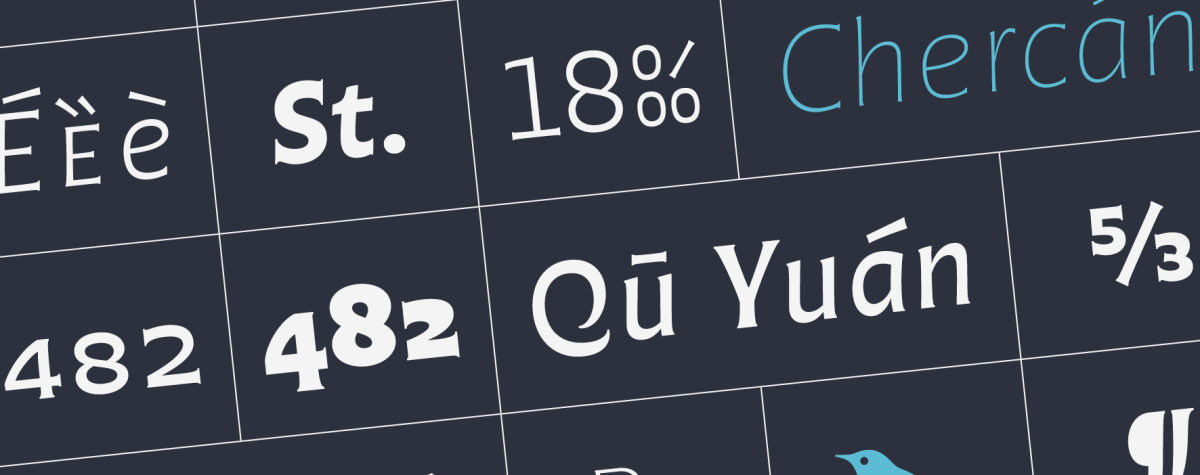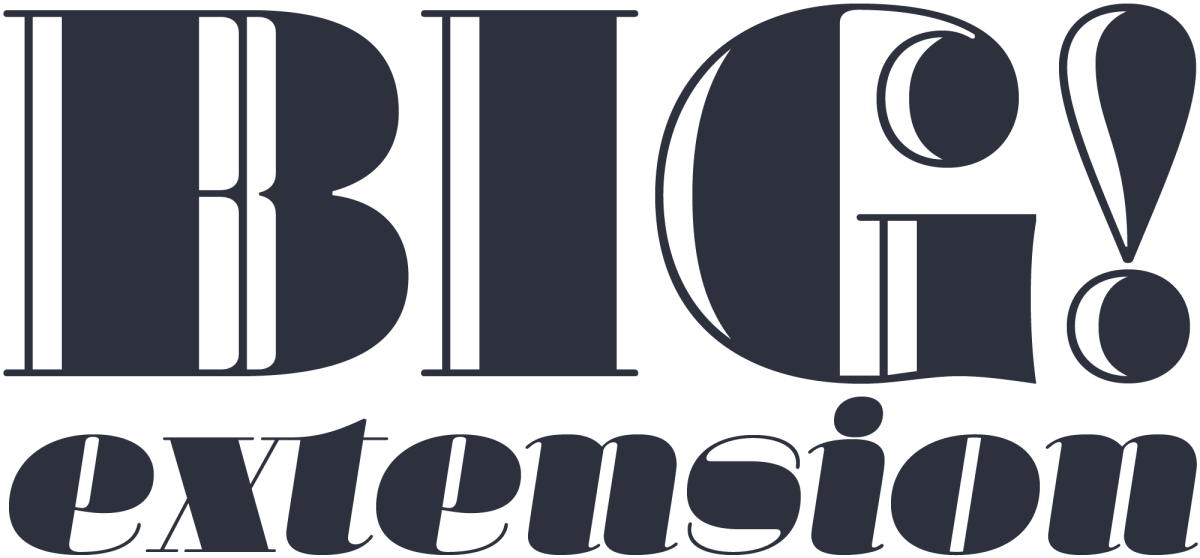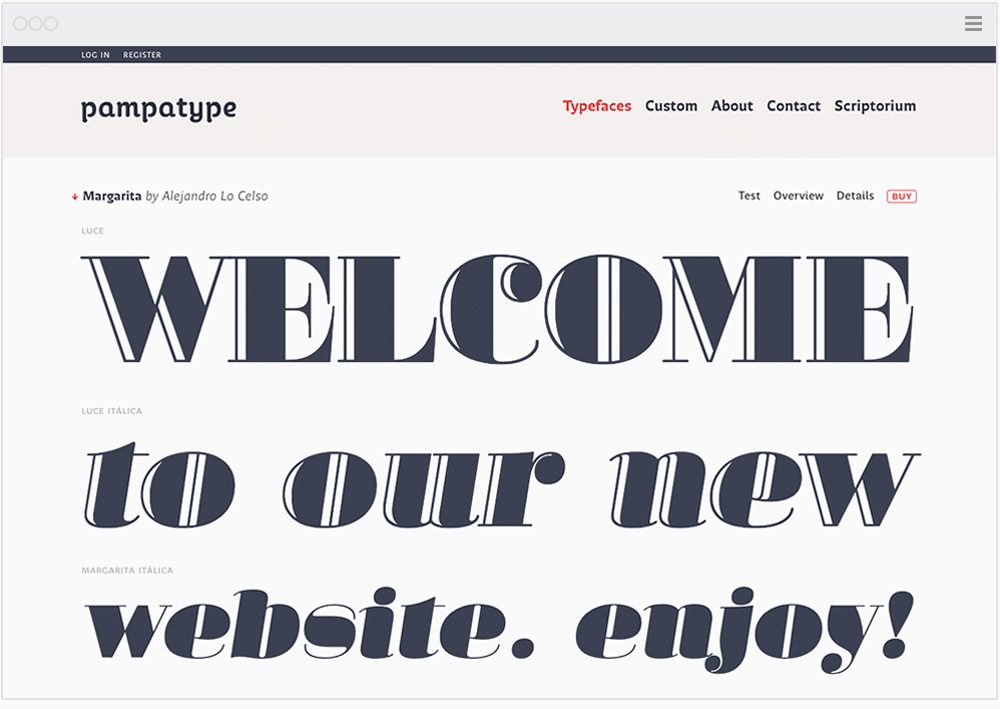
«Hacer y componer» de Francisco Gálvez (Editorial de la Universidad Católica de Chile) es, sin duda, un libro pedagógico. Como afirma Alejandro Lo Celso en el prólogo, se trata de un trabajo generoso, en el que se percibe la experiencia del autor en su actividad profesional. Como diseñador, tipógrafo, calígrafo y docente. Y, desde luego, esa generosidad se agradece. Read
We are proud of this project: The design of a typeface for the Universidad Nacional de Córdoba in Argentina, an educational institution of more than 400 years, the first in the country and one of the earliest in the continent. As part of the celebration for the hundred years of the University Reform, which occurred in this house in 1918, the UNC commissioned PampaType the design of a typeface to address their multiple communication needs. The resulting design, ‘Reforma’, is a multi-form family with diverse styles. In this article we share a bit of context, all the design process, some of our drawings and production details, and a few insights harvested throughout this 3-year fruitful experience. Read
Hoy en día los diseñadores somos responsables de una parte de la producción editorial que durante siglos había recaído en manos de especialistas: la composición tipográfica. Lamentablemente la evidencia indica que, en general, ésta sufre de un promedio de calidad mediocre. El problema no reside en las herramientas que tenemos a nuestra disposición —el software que usamos hoy día nos permite no sólo igualar, sino sobrepasar la calidad de la composición tipográfica de los siglos anteriores—; estriba en desaprovechar su potencial y, sobre todo, en no estar siquiera conscientes de que hay algo que necesita mejorar. Como nos recuerda Antoine de Saint-Exupéry, “lo esencial es invisible a los ojos”. El presente texto analiza esta cuestión y muestra la manera de resolverlo, mejorando la calidad de nuestro trabajo y reduciendo el tiempo invertido. Read
This typeface is named after the astonishing guitar player and singer Atahualpa Yupanqui, a central figure to Argentine folk music. ‘Don Ata’, as he was called, was a wise poet with a particularly sensitive view of the elements of nature as well as of the human condition, all of which he turned into compelling lyrics and magic songs. For years I dreamed about designing a typeface in his name. I imagined a firm, rough voice, though interpreted with delicate curves and a feel of warmth. After a few years of occasional sketching finally a spirit aroused in 2014. The initially vague forms turned into precise letterforms and with time into a family of fonts. Now the type Atahualpa finally sees the light. I’m happy. Here I invite you to unveil all the secrets behind the scene, discover the clues of the inspiration and the design process, and enjoy some footnotes from our design kitchen. Read
El universo de la tipografía está lleno de sutilezas y detalles, de formas que transmiten ideologías a través de sus trazos. El espécimen tipográfico es el mundo que antecede a la puesta en página y donde sobran pretextos para observar el color de la trama, el contraste, el espacio entre las líneas y las letras; es el lugar donde se originan las combinaciones infinitas de los signos que esperan inertes y que aún no toman sentido en un discurso, pero que son para disfrutarse. Esta reflexión pretende esbozar el vasto mundo de una herramienta tan importante, poco recurrida y bastante desaprovechada en nuestros días. Para entenderla, es preciso conocer sus orígenes y el desarrollo que tuvo en las distintas épocas. (Tercera y última entrega del texto.) Read
El universo de la tipografía está lleno de sutilezas y detalles, de formas que transmiten ideologías a través de sus trazos. El espécimen tipográfico es el mundo que antecede a la puesta en página y donde sobran pretextos para observar el color de la trama, el contraste, el espacio entre las líneas y las letras; es el lugar donde se originan las combinaciones infinitas de los signos que esperan inertes y que aún no toman sentido en un discurso, pero que son para disfrutarse. Esta reflexión pretende esbozar el vasto mundo de una herramienta tan importante, poco recurrida y bastante desaprovechada en nuestros días. Para entenderla, es preciso conocer sus orígenes y el desarrollo que tuvo en las distintas épocas. (Esta es la segunda de tres entregas del texto.) Read
El universo de la tipografía está lleno de sutilezas y detalles, de formas que transmiten ideologías a través de sus trazos. El espécimen tipográfico es el mundo que antecede a la puesta en página y donde sobran pretextos para observar el color de la trama, el contraste, el espacio entre las líneas y las letras; es el lugar donde se originan las combinaciones infinitas de los signos que esperan inertes y que aún no toman sentido en un discurso, pero que son para disfrutarse. Esta reflexión pretende esbozar el vasto mundo de una herramienta tan importante, poco recurrida y bastante desaprovechada en nuestros días. Para entenderla, es preciso conocer sus orígenes y el desarrollo que tuvo en las distintas épocas. (Esta es la primera de tres entregas del texto.) Read
This essay was the original dissertation I wrote for the MA in Typeface Design at the University of Reading, UK, 2000. Since then it has met some popularity. It was slightly adjusted years later for its publication under TypeCulture.com and also under lpdme.org. Of course some references may feel out of date by now. However I believe its ideas and insights are mostly perennial. Read
Portada de Tipografía en Latinoamérica editado por Blucher, San Pablo, 2013. target: _blank
Segunda y última entrega del 1er capítulo del libro “Tipografía en Latinoamérica. Orígenes e identidad”, editado por Cecilia Consolo y publicado por Blucher en Brasil, 2013. Sus editores han aceptado amablemente publicarlo aquí. Es una mirada retrospectiva y muy personal de la historia de la tipografía europea desde Gutenberg a la era digital. Pretender abarcar semejante lapso de tiempo en tan poco espacio habilita a posibles exageraciones y reduccionismos. El objetivo ha sido intentar provocar al lector a continuar su propia búsqueda. La primera parte toca en los episodios significativos desde el tipo móvil alemán de fines del s. XV, la escuela humanista italiana, Jenson, Manucio y Griffo, la Edad de Oro francesa del s. XVI, de Tory a Garamond y Robert Granjon. La 2da parte retoma en el barroco neerlandés del s. XVII e intenta referir los hitos fundamentales de la producción británica, ibérica, alemana, y holandesa, incluido el empuje en tipo digital de La Haya. A modo didáctico, imágenes comparativas de anatomía y evolución de las formas tipográficas se han sumado al final de esta 2da parte. (Escrito en Ciudad de México, 10 de enero de 2010.) Read
Portada de Tipografía en Latinoamérica editado por Blucher, San Pablo, 2013. target: _blank
Primera de dos entregas del 1er capítulo del libro “Tipografía en Latinoamérica. Orígenes e identidad”, editado por Cecilia Consolo y publicado por Blucher en Brasil, 2013. Sus editores han aceptado amablemente publicarlo aquí. Es una mirada retrospectiva y muy personal de la historia de la tipografía europea desde Gutenberg a la era digital. Pretender abarcar semejante lapso de tiempo en tan poco espacio habilita a posibles exageraciones y reduccionismos. El objetivo ha sido intentar provocar al lector a continuar su propia búsqueda. La primera parte toca en los episodios significativos desde el tipo móvil alemán de fines del s. XV, la escuela humanista italiana, Jenson, Manucio y Griffo, hasta la Edad de Oro francesa del s. XVI, de Tory a Garamond y Robert Granjon. La 2da parte retoma en el barroco neerlandés del s. XVII e intenta referir los hitos fundamentales de la producción británica, ibérica, alemana, y holandesa, incluido el empuje en tipo digital de La Haya. A modo didáctico, imágenes comparativas de anatomía y evolución de las formas tipográficas en Occidente se han sumado al final de la 2da parte. (Escrito en Ciudad de México, 10 de enero de 2010.) Read
This detectivesque chronicle written by journalist Feike de Jong reopened the chests of the mysterious case of an early 17th century punch cutter from The Netherlands named Nicolaes Briot. Originally published by the Czech magazine TYPO, in their issue of Spring 2011, the editors have kindly allowed us to reproduce it here. Stay tuned, the second part of this story is under editing. (The Briot project is part of a wider revival program on historical sources carried out by PampaType since 2004. In the case of Briot, it has been so far the result of a collaboration between John Lane and Alejandro Lo Celso.) Read
The design of the Amster type family implied a process of creation and maturing of seven years. In this article Francisco Gálvez, its designer, gives us some of his various insights around that process, its referents and inspirations. Read
Since its release Margarita have met much sympathy. No doubt it is a passionate type. One can easily relate its anatomy to Romanticism, Neoclassicism, or for that matter to the deeply emotional character everyone ascribe to Italians! a bit of a cliché… Read